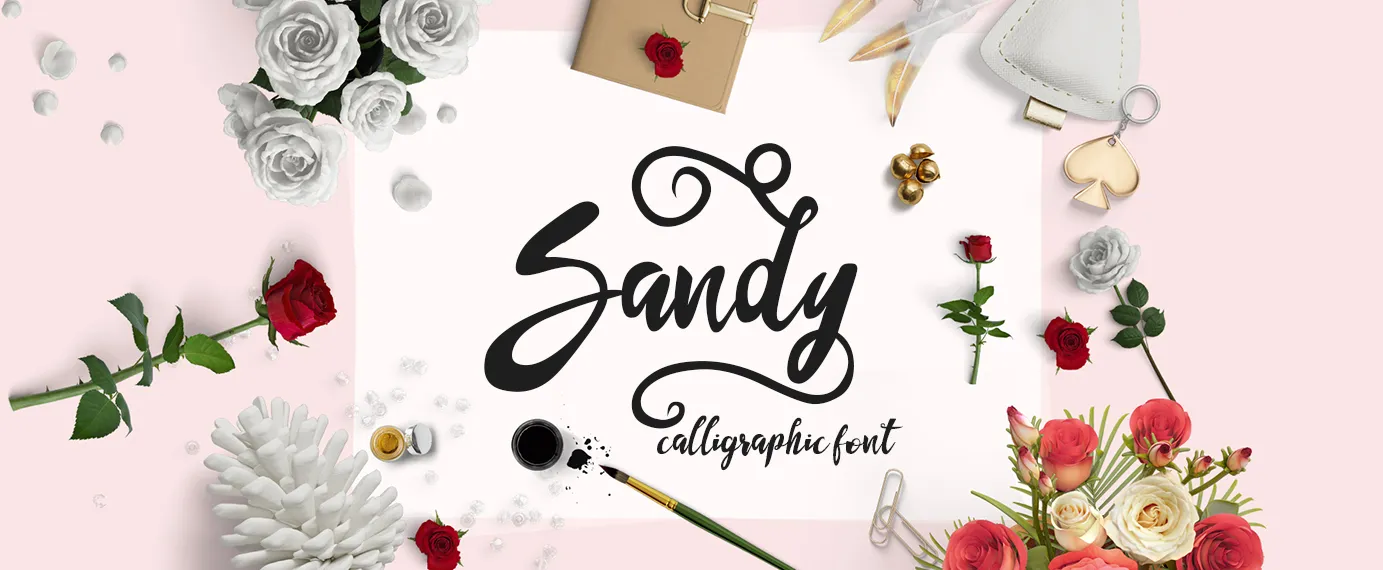
Sandy Font – Download Grátis
Introduzimos a Sandy Font, uma elegante fonte Brush que você pode baixar gratuitamente e personalizar para projetos pessoais. Ela foi cuidadosamente criada pelo designer Hamilton à base de desenhos feitos à mão, ideal para quem está começando com as cores e formas da fonte em trabalhos de design e arte. Essa versão leve da Sandy é perfeita para testes e experimentações visuais antes do uso final em qualquer projeto pessoal ou profissional. Aproveite sua liberdade criativa enquanto mantém a beleza natural e única desta fonte, uma jóia entre as muitas disponíveis na FontBundles.net.